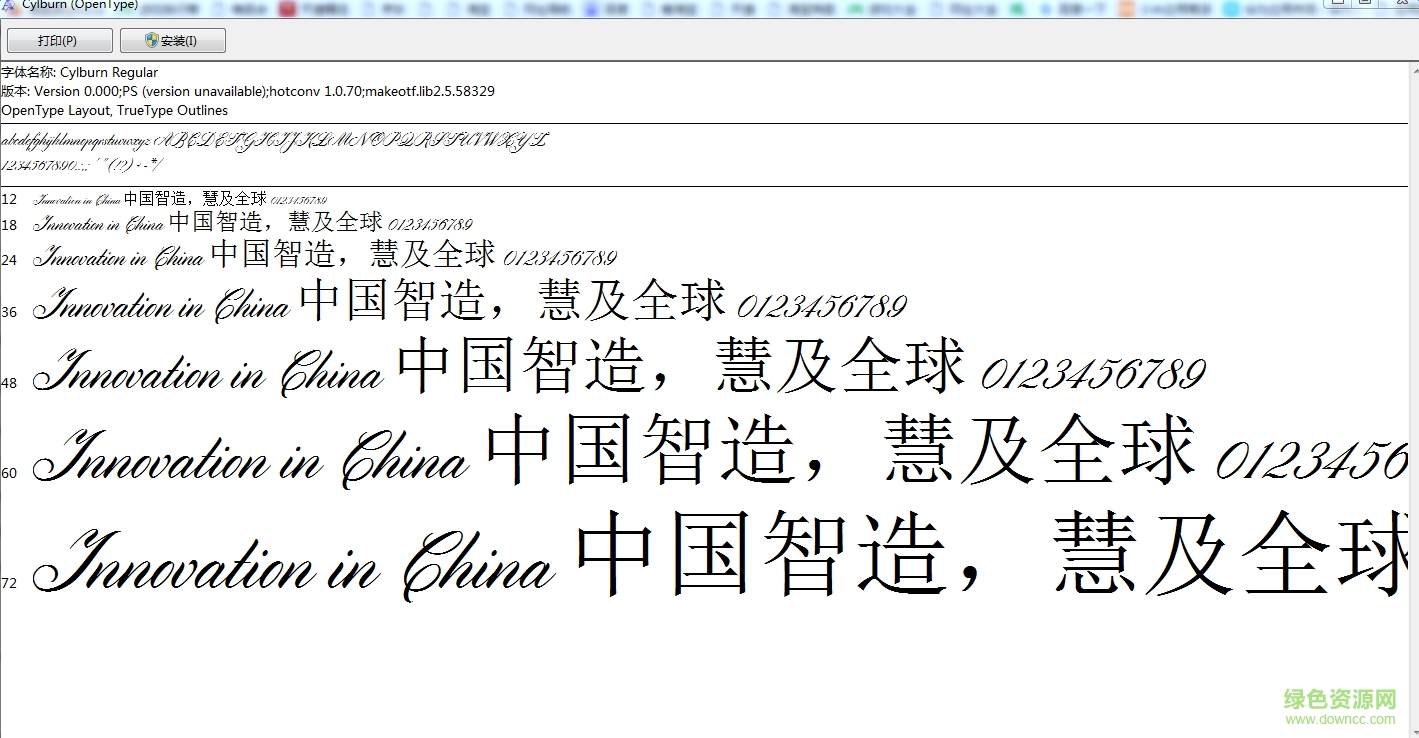
cylburn字體是一款斜體的英文字體,線條連綿一氣呵成,字形瀟灑飄逸,清新精致,看上去十分美觀!喜歡這款字體的朋友快來綠色資源網(wǎng)下載收藏吧!
cylburn字體簡單靈動,使人感覺優(yōu)雅有品質(zhì)。整套字具有現(xiàn)代感。適合畫冊標題、海報設(shè)計、廣告宣傳等場合使用。